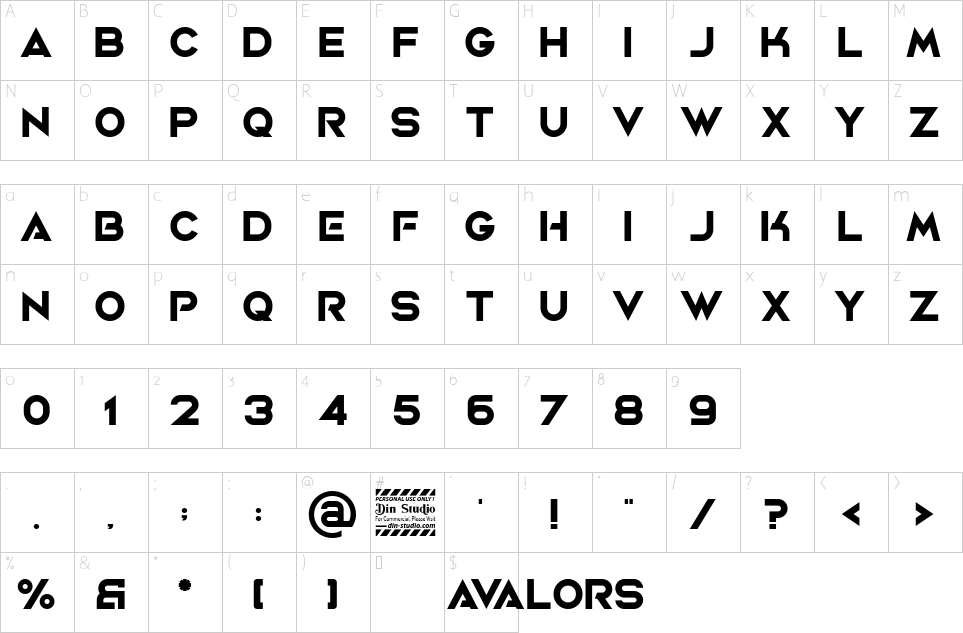
Descubra a beleza da Avalors font, uma fonte de design elegante e naturalmente sofisticada. Desenvolvida por Donis Miftahudin, a Avalors é uma escolha perfeita para designers que buscam uma fonte moderna com nuances de elegância. Seja para títulos ou texto detalhado, Avalors oferece um toque de classe. Se você está procurando por uma fonte de qualidade para trabalhos impressos ou projetos digitais, não hesite em experimentar Avalors. Ainda melhor, esta fonte está disponível gratuitamente para Windows e Mac, com downloads recentes de 619 usuários. Engane-se se pensar que Avalors é apenas uma fonte mais, ela traz consigo um design que complementará qualquer projeto. Em sua busca por uma fonte de qualidade e elegância, Avalors é uma fonte que não pode ficar fora da sua lista de possíveis.